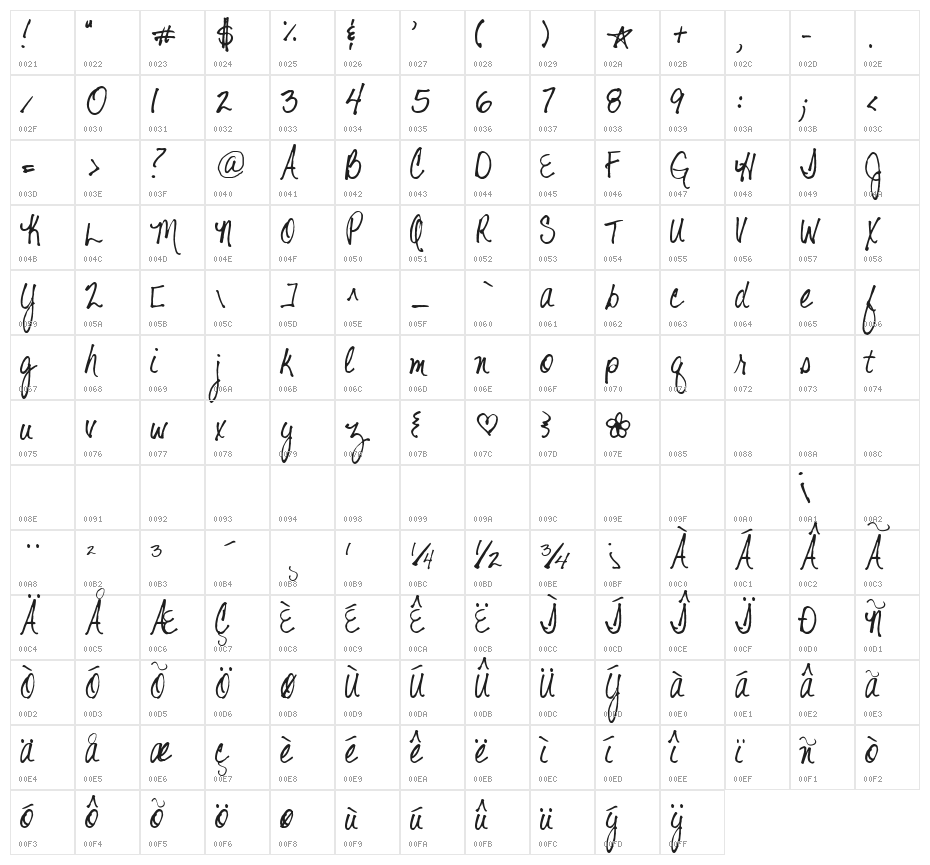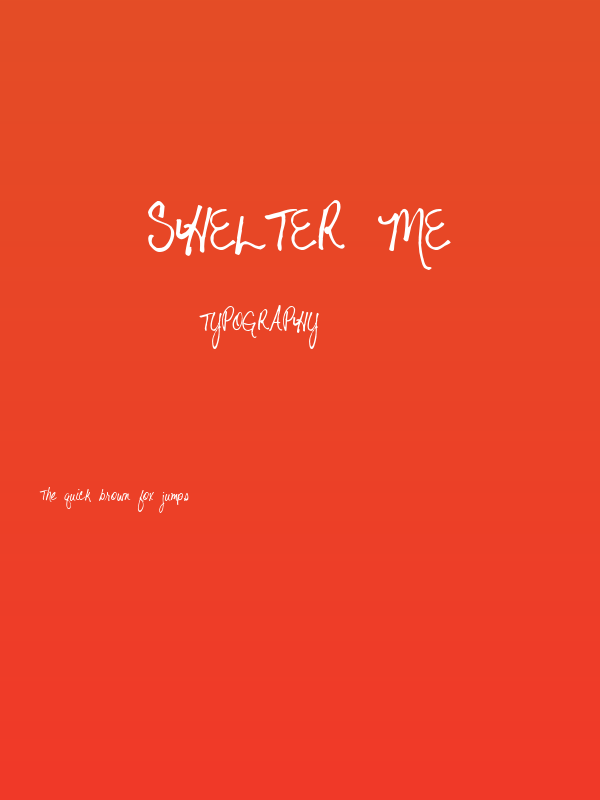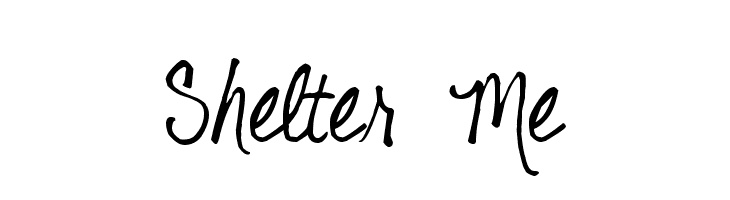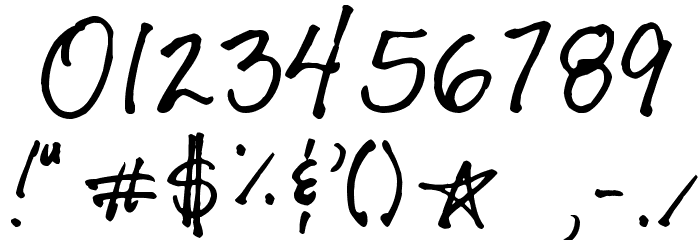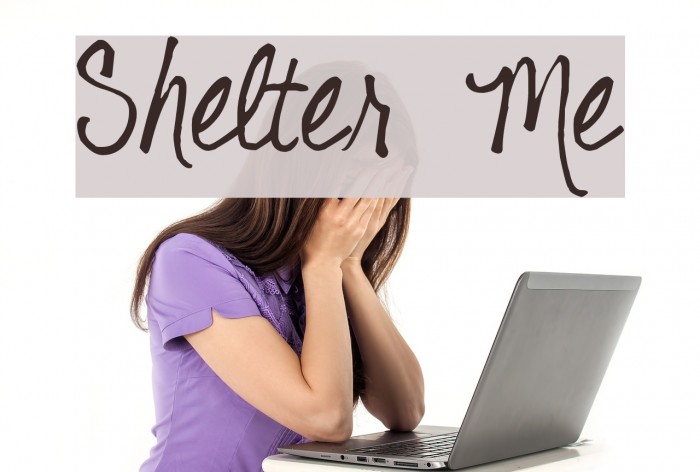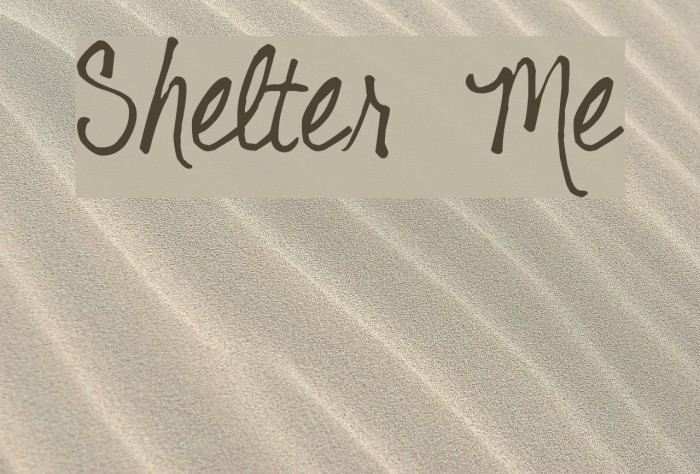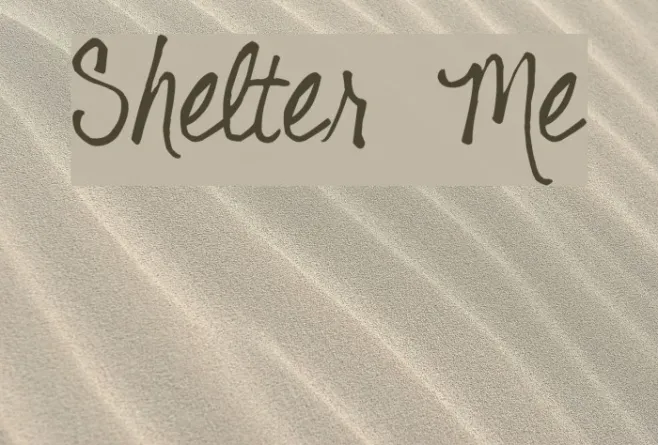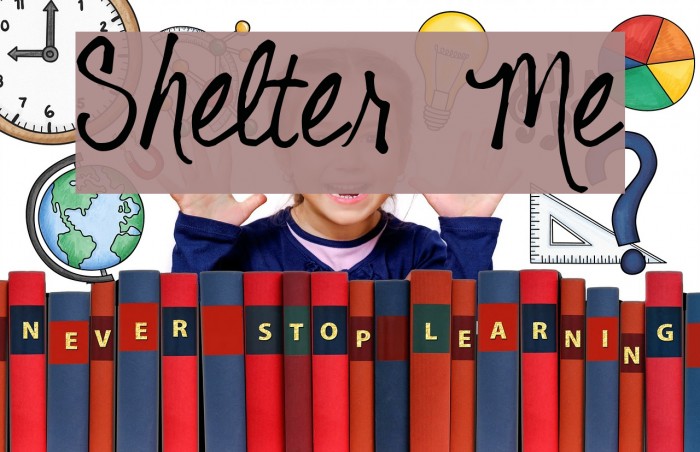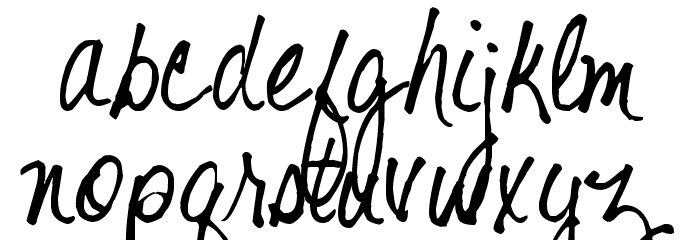
Shelter Me Font
| Caso d'uso | Logos, Headlines, Creative projects |
| Progetti proposti | Ideal for greeting cards, personal branding, artistic posters, and creative invitations. |